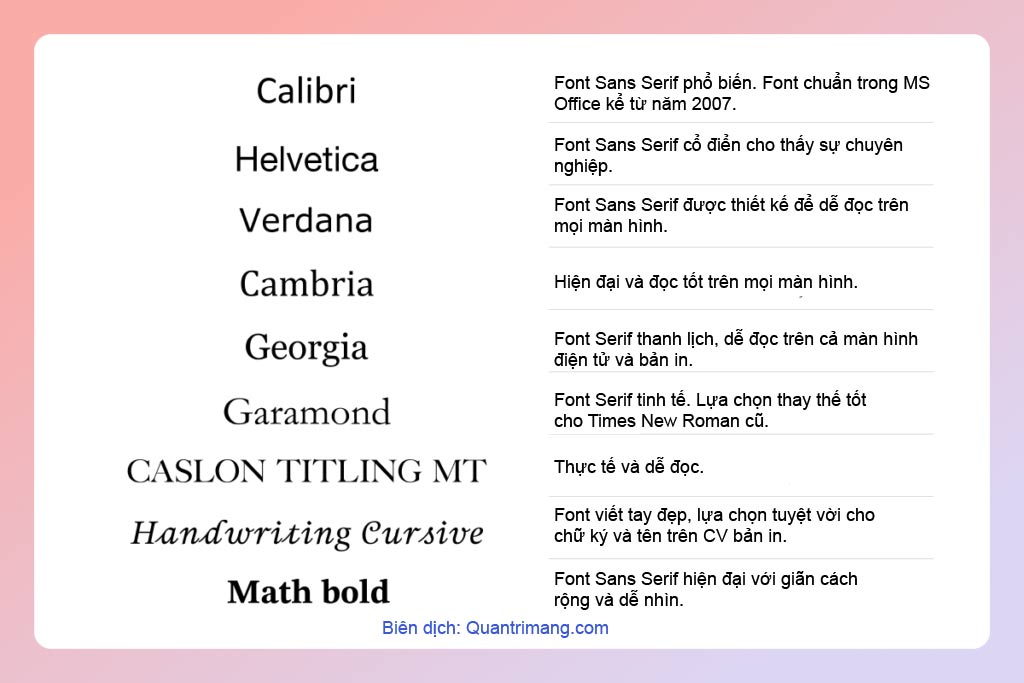
Font chữ CV đẹp, giúp bạn gây ấn tượng với nhà tuyển dụng
Các nhà tuyển dụng xem hàng trăm bản sơ yếu lý lịch mỗi tuần. Điều này có nghĩa là bất kể sơ yếu lý lịch của bạn được viết tốt như thế nào, cái nhìn đầu tiên sẽ quyết định liệu họ có dành thời gian để tìm hiểu thêm về bạn hay không.
Font chữ CV tốt nhất
Vì thiết kế một hồ sơ xin việc hấp dẫn là chìa khóa để tạo ấn tượng tuyệt vời đầu tiên, nên việc chọn font chữ  CV hay sơ yếu lý lịch rất quan trọng. Đó là lý do tại sao bài viết sẽ tổng hợp những font chữ CV giúp bạn nổi bật trong một thị trường việc làm cạnh tranh như hiện nay.
Tại sao lựa chọn font chữ quan trọng khi viết CV?
Nghiên cứu cho thấy họ chỉ dành từ 6 đến 8 giây để xem từng bản sơ yếu lý lịch nhận được. Để họ có thể nhanh chóng hiểu được bạn là người như thế nào, bạn cần làm cho bản sơ yếu lý lịch của mình cực kỳ dễ đọc.
Điều quan trọng cần nhớ là mặc dù một số phông chữ có thể trông tuyệt vời khi đưa cho bạn bản CV đã in, nhưng chúng có thể hiển thị kém trên màn hình máy tính nhỏ hơn. Hãy kiểm tra phông chữ của bạn trên nhiều thiết bị để đảm bảo rằng người tuyển dụng và người sử dụng lao động có thể dễ dàng chọn ra thông tin chính.
Lựa chọn font chữ tốt nhất đối với các ngành nghề khác nhau
Trong nhiều ngành, font chữ CV tốt nhất là phông chữ truyền tải tính chuyên nghiệp và cảm giác truyền thống. Ví dụ, các ngành như luật và tài chính thường đánh giá cao phông chữ Serif cổ điển như Times New Roman. Nhiều nghiên cứu thậm chí còn chỉ ra rằng phông chữ quen thuộc với nhà tuyển dụng có thể thúc đẩy khả năng hiểu và tăng tốc độ đọc.
Tuy nhiên, những phông chữ truyền thống này có thể bị lạm dụng và khiến chúng không nổi bật khi được xem trên các chương trình khác nhau. Với ngành công nghiệp sáng tạo hoặc hiện đại hơn, font chữ kiểu dáng nghệ thuật sẽ là lựa chọn tốt hơn.
Khi chọn phông chữ, bạn cũng cần lưu ý đến Hệ thống theo dõi ứng viên (ATS). Phần mềm ATS thường được các công ty sử dụng để quét sơ yếu lý lịch và cho phép nhà tuyển dụng lập danh sách ứng viên.
Mặc dù một số phông chữ nghệ thuật có thể được ghép nối với các phông chữ cổ điển cho những thứ như tiêu đề hoặc tên của bạn, nhưng khi sử dụng hàng loạt, chúng có thể khiến ATS khó quét hồ sơ. Để có kết quả tối ưu, hãy sử dụng phông chữ có kiểu dáng khi gửi sơ yếu lý lịch trực tiếp cho khách hàng và phông chữ chuẩn hơn khi tải lên ATS.
9 font chữ CV tốt nhất
Font chữ CV tốt nhất
Các kiểu font chữ CV tốt nhất
Các phông chữ tốt nhất cho CV thường đến từ hai loại chính. Sans Serif hoặc Serif. Ngoài ra còn có các phông chữ được tạo kiểu có thể giúp bạn nổi bật.
Font Sans-Serif
Sans Serif là phông chữ rõ ràng, hiện đại được thiết kế để có thể đọc được trên mọi màn hình kỹ thuật số. Đây là lựa chọn tuyệt vời để tạo sơ yếu lý lịch mà bạn tải lên ATS.
• Calibri: Tùy chọn chính. Năm 2007, Calibri đã thay thế Times New Roman và Arial trong Word và PowerPoint. Bản chất tròn trịa của nó được thiết kế để làm mềm mại và hấp dẫn đối với người đọc trong khi vẫn duy trì khả năng đọc tuyệt vời trên màn hình kỹ thuật số.
• Helvetica: Dấu ấn của Thụy Sĩ trong thiết kế đồ họa hiện đại về phông chữ. Được phát triển vào năm 1957 nhưng vẫn phổ biến cho đến ngày nay, Helvetica cung cấp một phiên bản giản dị và nghệ thuật nhưng vẫn chuyên nghiệp của phông chữ Sans Serif.
• Verdana: Được thiết kế với khoảng cách rộng rãi để duy trì khả năng đọc tốt ở kích thước nhỏ hơn trên màn hình có độ phân giải thấp hơn. "Ngoại hình" sáng sủa khiến nó trở thành một trong những phông chữ tốt nhất cho nội dung CV chính.
Lựa chọn font CV tốt nhất
Font Serif
Font Serif như Times New Roman có giao diện truyền thống hơn. Điều này khiến chúng trở nên phổ biến trong các lĩnh vực chính thức như pháp lý và tài chính.
• Cambri: Phông chữ chắc chắn với độ tương phản cao để duy trì khả năng đọc ở cả kích thước nhỏ và lớn. Phiên bản hiện đại của Times New Roman này là phông chữ tốt nhất cho CV nếu bạn đang tìm kiếm phong cách cổ điển.
• Georgia: Dựa trên thiết kế kiểu chữ in, font Serif thanh lịch này ban đầu được thiết kế vào năm 1993. Các đặc điểm nổi bật của nó đọc tốt ở kích thước nhỏ hơn và trên màn hình có độ phân giải thấp.
• Garamond: Được thiết kế tại Paris vào thế kỷ XVI, phông chữ cổ điển này đã phổ biến trong nhiều thế kỷ, đặc biệt là để sử dụng trong phần nội dung chính của sách. Garamond mang đến giao diện tinh tế và là sự thay thế tuyệt vời cho Times New Roman.
Phông chữ có kiểu dáng
Sau đây là một số phông chữ có kiểu dáng đẹp nhất cho CV:
• Carlson Titling: Phông chữ in hoa toàn bộ được xác định bởi khả năng điền vào các khoảng trống nhỏ hơn một cách thoải mái. Phổ biến cho logo, đây là lựa chọn tốt cho tiêu đề trên CV vì nó giản dị nhưng vẫn nổi bật.
• Chữ viết tay: Được thiết kế để trông giống như văn bản viết tay theo kiểu chữ thảo. Có thể sử dụng cho các tính năng như tên của bạn trên CV được in trong các lĩnh vực thông thường như thiết kế hoặc làm chữ ký số của người giới thiệu trong thông tin hỗ trợ.
• Math bold: Kiểu chữ in đậm trông chuyên nghiệp tương tự như Times New Roman nhưng đậm hơn. Lý tưởng cho các tiêu đề như tên nơi làm việc trước đây.